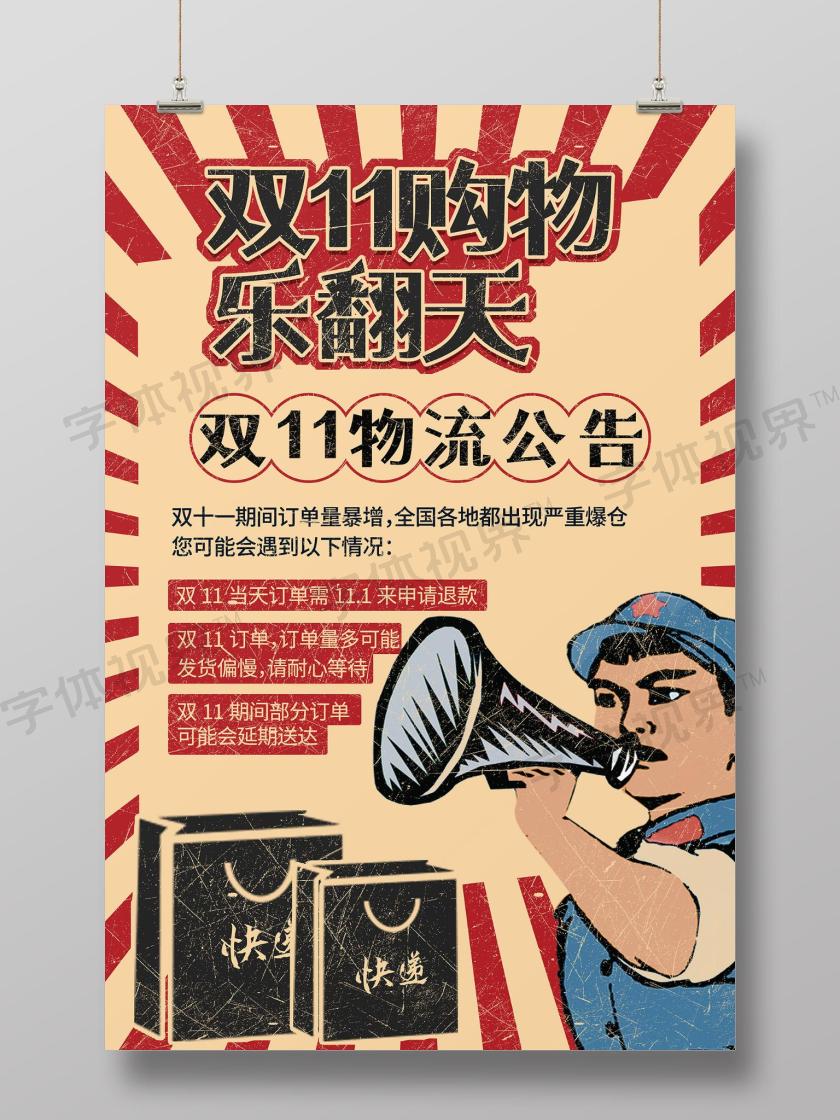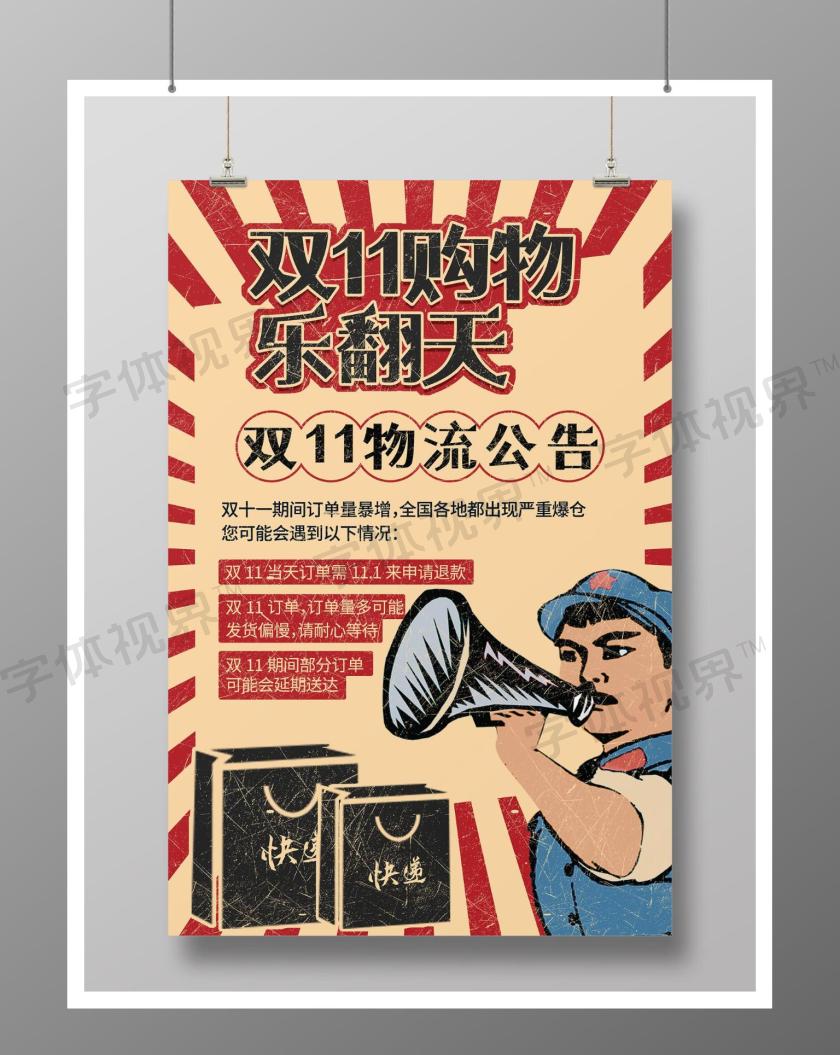
双十一11大抢购宣传海报
这是一张关于双十一抢购海报设计图片,创意风格设计,以大红色为主色调,信封为设计元素,设计成双十一抢购海报模板,主体文字图片皆可替换修改,也可用于双十一抢购海报、双十海报、抢购海报、宣传海报、十一海报、双十一宣传海报、十一宣传海报模板素材,格式为PSD,作品编号:516523,尺寸为3543*5315像素,欢迎会员免费下载。